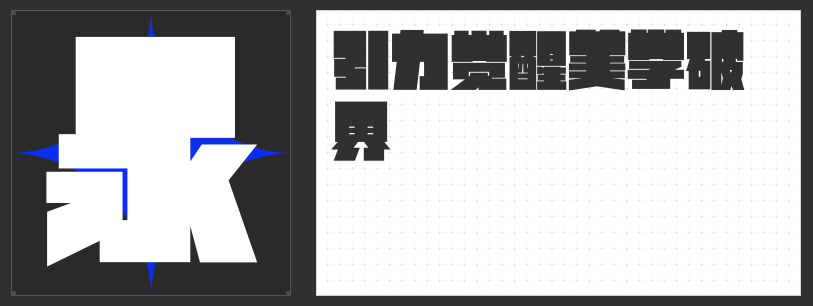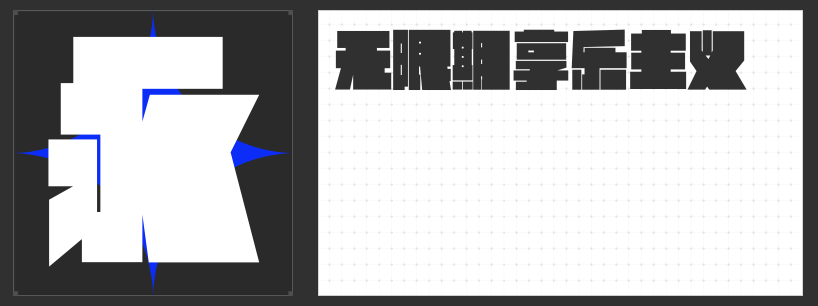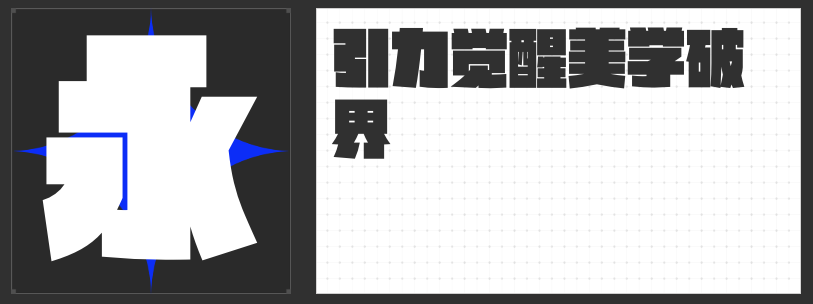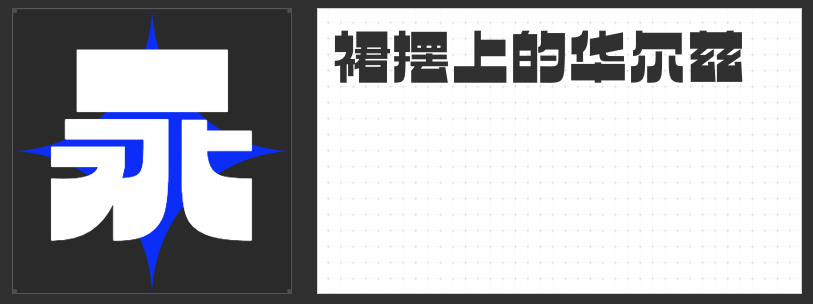
探索视觉新境界:逆反差字体的独特魅力与推荐
在数字设计日益精进的今天,字体选择不再仅仅局限于清晰可读,更成为了表达个性、营造氛围的重要工具。逆反差字体,这一打破常规的字体类型,正以其独特的视觉冲击力,引领着设计界的新风尚。
励字逆反差圆舞简 超级黑
这款字体巧妙融合了逆反差的设计理念与圆润优雅的线条,再辅以超级黑的深邃字重,创造出一种既对比鲜明又和谐统一的视觉效果。在亮色或浅色背景下,其黑色的字体仿佛自带光环,不仅保证了文字的高辨识度,更增添了几分神秘与高级感。
励字逆反差圆舞简 超级黑在多个设计领域均有着广泛的应用前景。在品牌标识设计中,它能够凸显品牌的独特性与力量感;在广告海报中,它则能瞬间抓住观众的眼球,成为视觉的焦点;而在书籍装帧或网页设计中,这款字体又能为整体设计增添一抹独特的韵味,提升阅读体验。
励字跨界黑简 超级黑
励字跨界黑简 超级黑以其极致的黑白对比,展现了逆反差字体的独特魅力。在浅色或亮色背景下,其深邃的黑色字体如同夜空中最亮的星,不仅确保了文字的高辨识度,更赋予了设计作品以强烈的视觉冲击力和深度感。同时,其简洁流畅的线条与坚实的字体结构,使得每一个字都充满了力量与稳重,仿佛能够穿透屏幕,直击人心。
励字跨界黑简 超级黑在设计界的应用极为广泛。在品牌塑造中,它能凸显品牌的独特个性和高端质感;在广告设计中,它能迅速吸引观众的注意力,成为焦点所在;在书籍装帧、网页设计及各类印刷品中,它都能以其独特的风格,为作品增添一抹不可磨灭的印记。
励字宽边黑简 超级黑
励字宽边黑简 超级黑以其独特的宽边设计,将黑色字体与背景之间的界限划分得更为清晰,从而在视觉上形成了更为强烈的反差效果。这种设计不仅增强了文字的辨识度,更使得每一个字都仿佛被精心雕琢的艺术品,展现出一种沉稳而不失灵动的美感。在浅色或亮色背景下,这款字体更是能够脱颖而出,成为视觉的焦点。
在设计领域,这款字体的应用前景极为广阔。无论是品牌标识、广告宣传,还是书籍装帧、网页设计,它都能以其独特的风格为作品增添一抹独特的韵味。特别是在需要强调力量感、稳重感或高端感的场景中,励字宽边黑简 超级黑更是能够发挥出其独特的优势,为设计作品赋予更加深刻的内涵和气质。
励字造大头黑 超级粗
励字造大头黑 超级粗以其超粗的笔画和放大的字头设计,打破了传统字体的常规束缚,呈现出一种前所未有的视觉震撼。在浅色或亮色背景下,这款字体的黑色粗体犹如巨石投湖,瞬间激起视觉的涟漪,让人无法忽视。
励字造大头黑 超级粗的应用领域极为广泛。在品牌塑造中,它能够凸显品牌的独特个性和力量感,让人过目难忘;在广告设计中,它则是吸引眼球、传递信息的得力助手;而在海报、包装等印刷品中,它更是能够以其粗犷而不失精致的设计,为作品增添一抹独特的魅力。
逆反差字体的魅力在于它们能够突破常规的视觉习惯,创造出令人难忘的设计效果。但值得注意的是,在使用时也要考虑到阅读舒适度和整体设计的和谐性,避免过度使用导致视觉疲劳。选择适合的逆反差字体,让你的设计作品在众多平凡中脱颖而出,成为视觉的焦点。